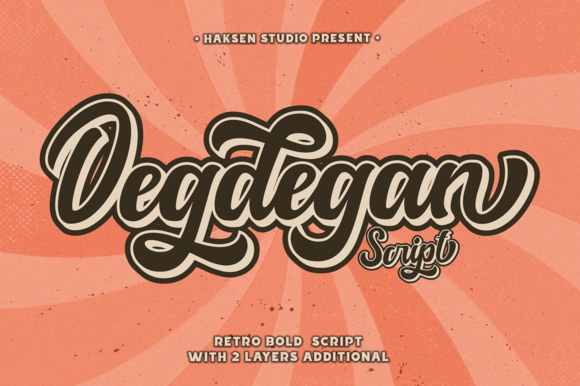
Creativefabrica Degdegan Font
[Creativefabrica] Degdegan Font
Дегдеган - это винтажный стильный и смелый рукописный шрифт, созданный для придания стильного штриха вашим заголовкам и логотипам проектов. Этот шрифт читается как сильный, уверенный и динамичный и может добавить тонны ностальгического характера вашим дизайнам.